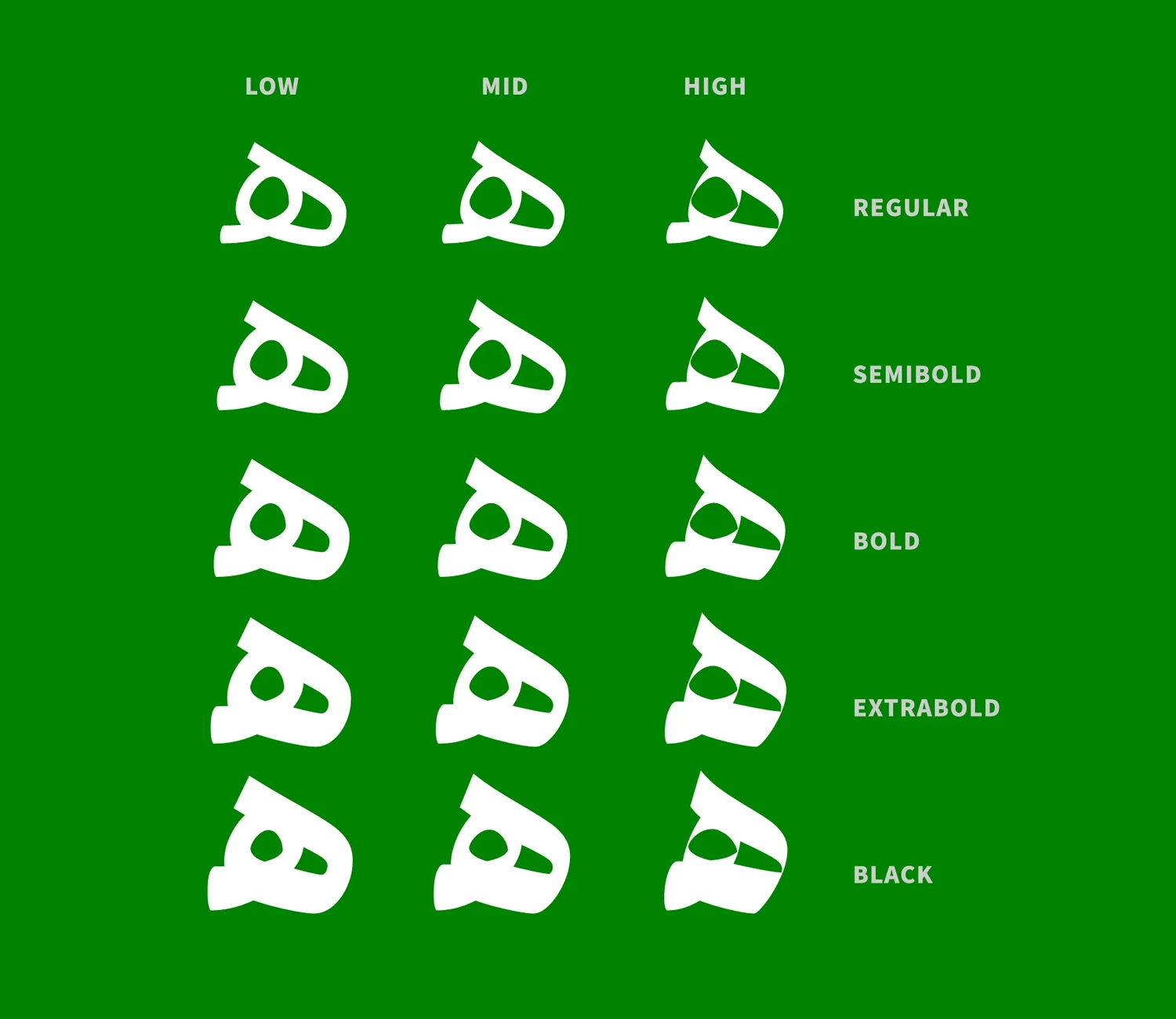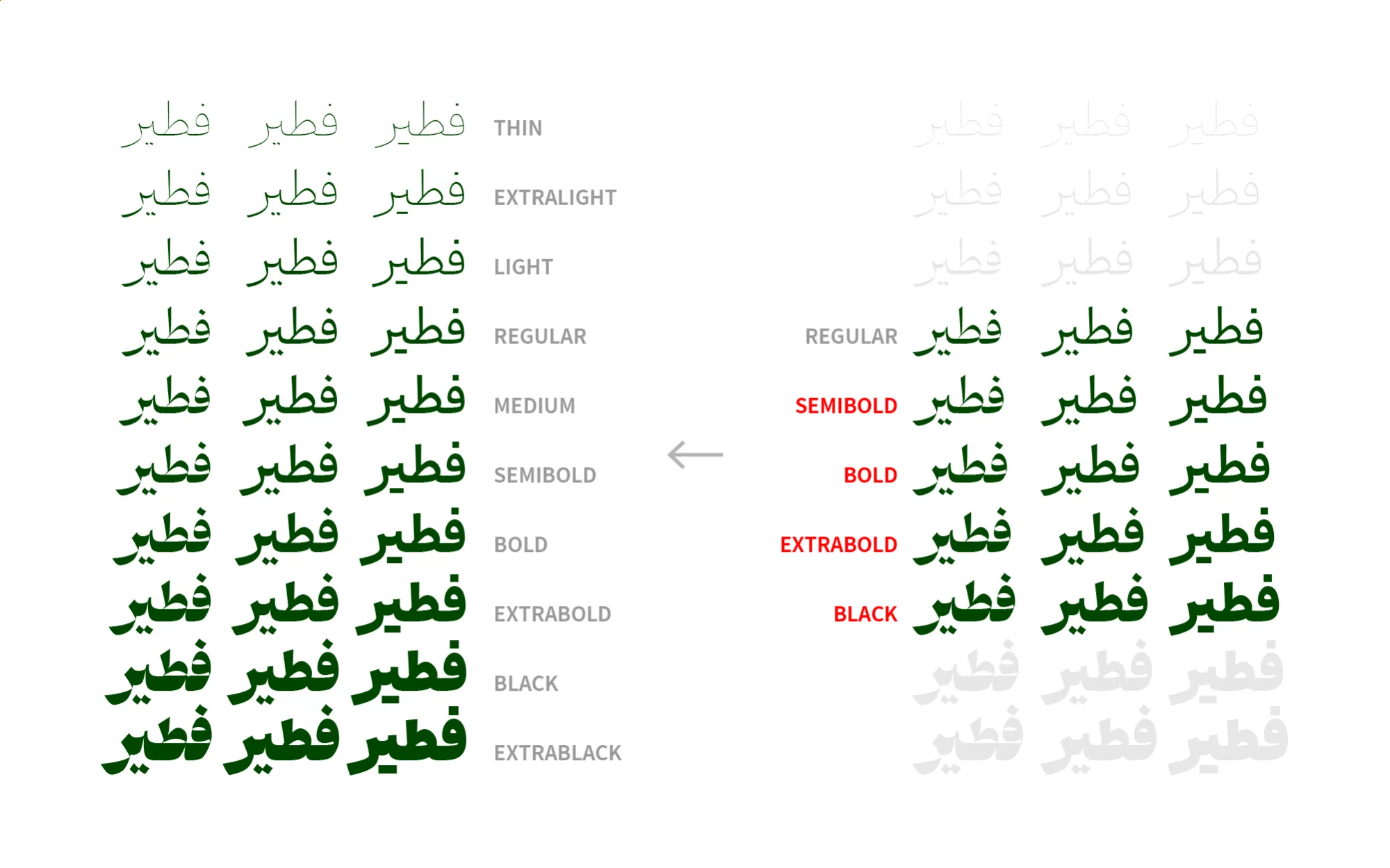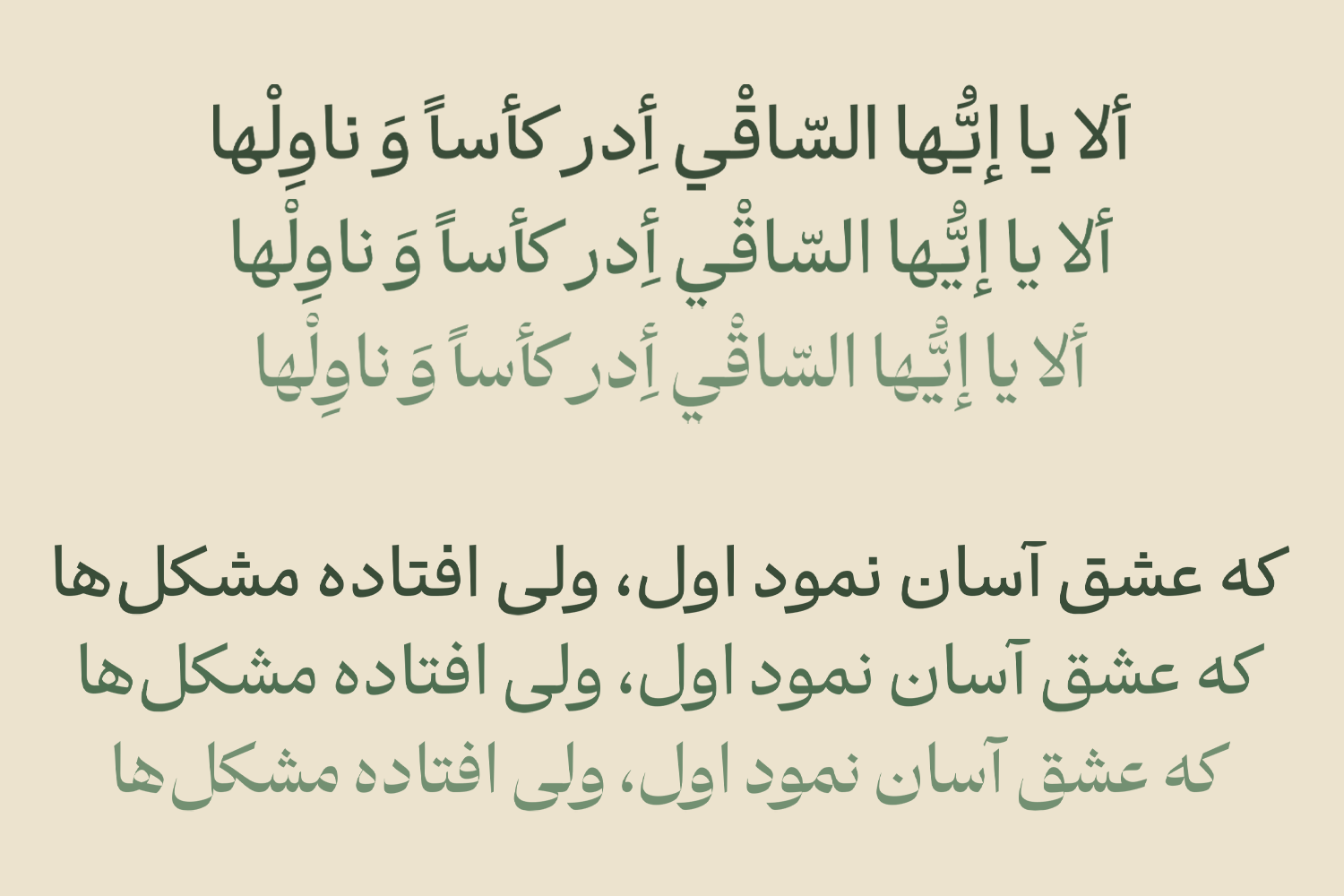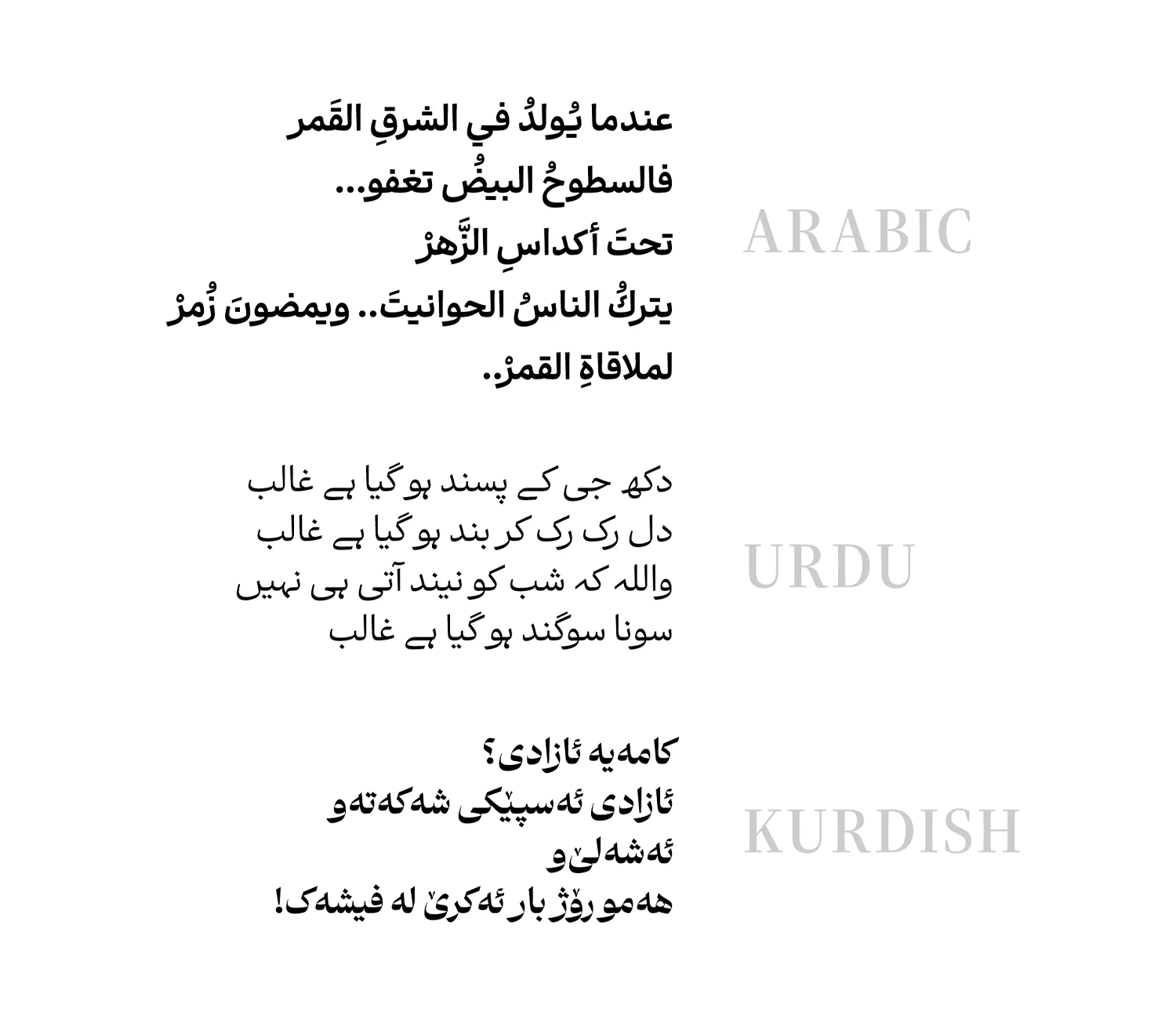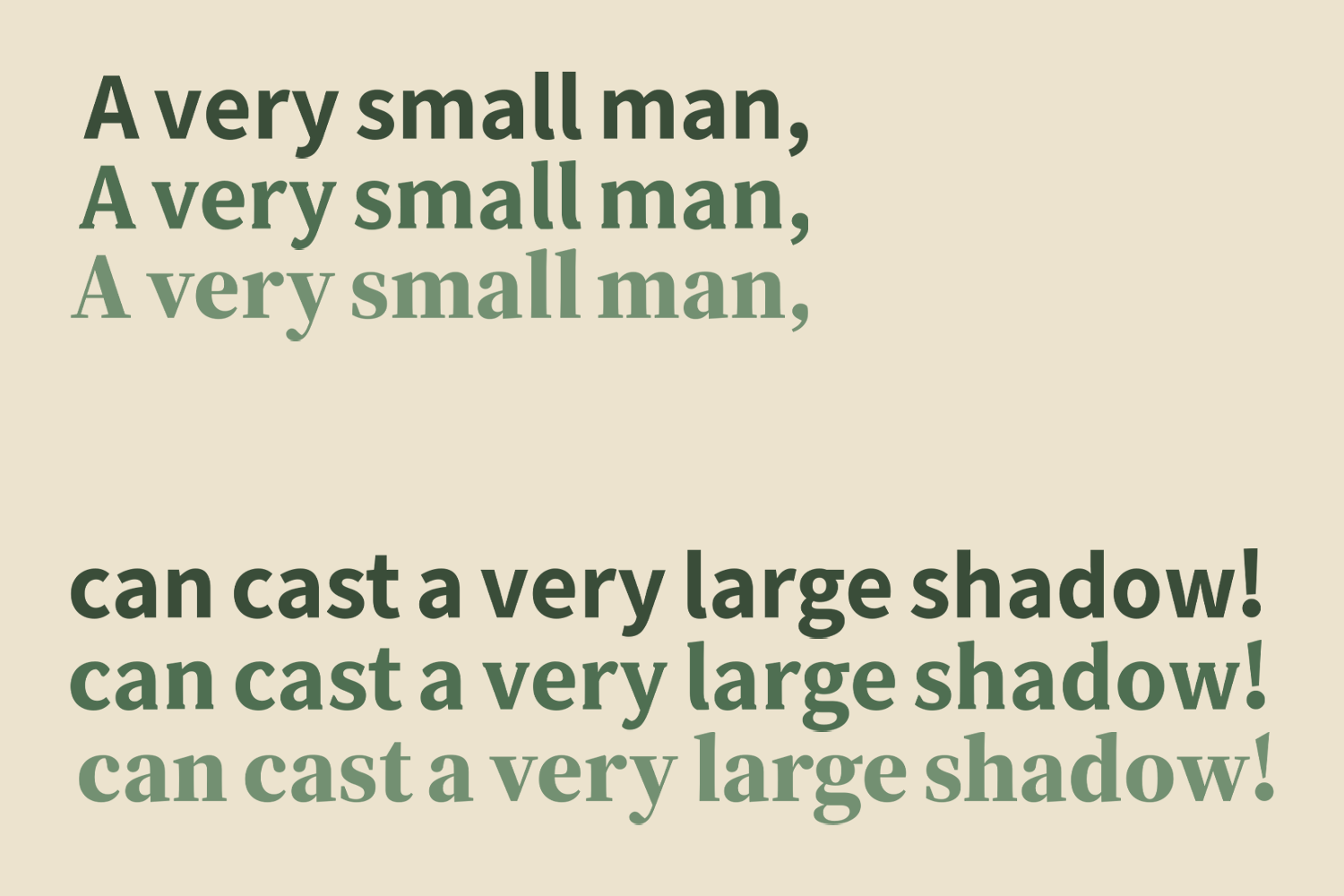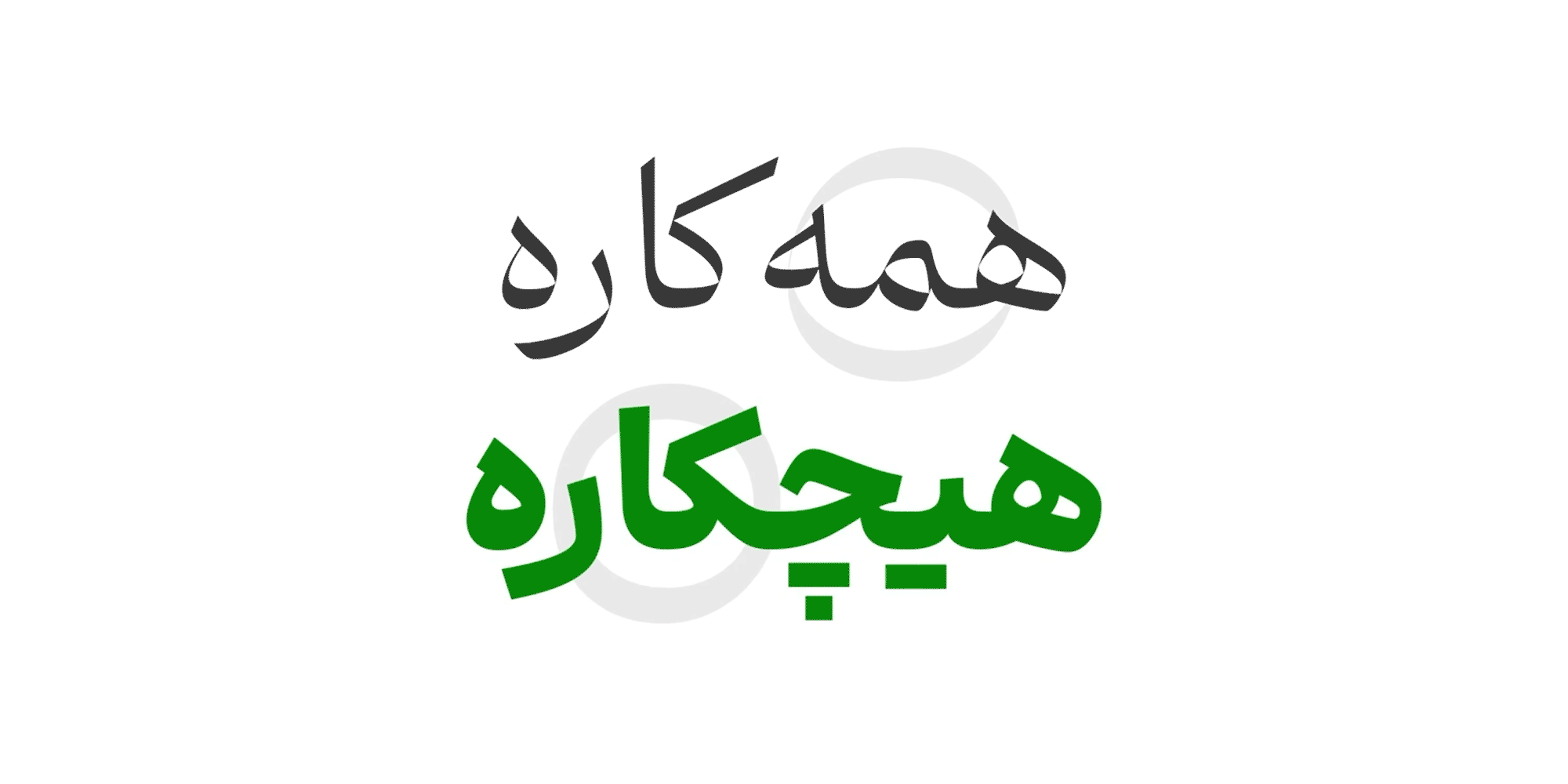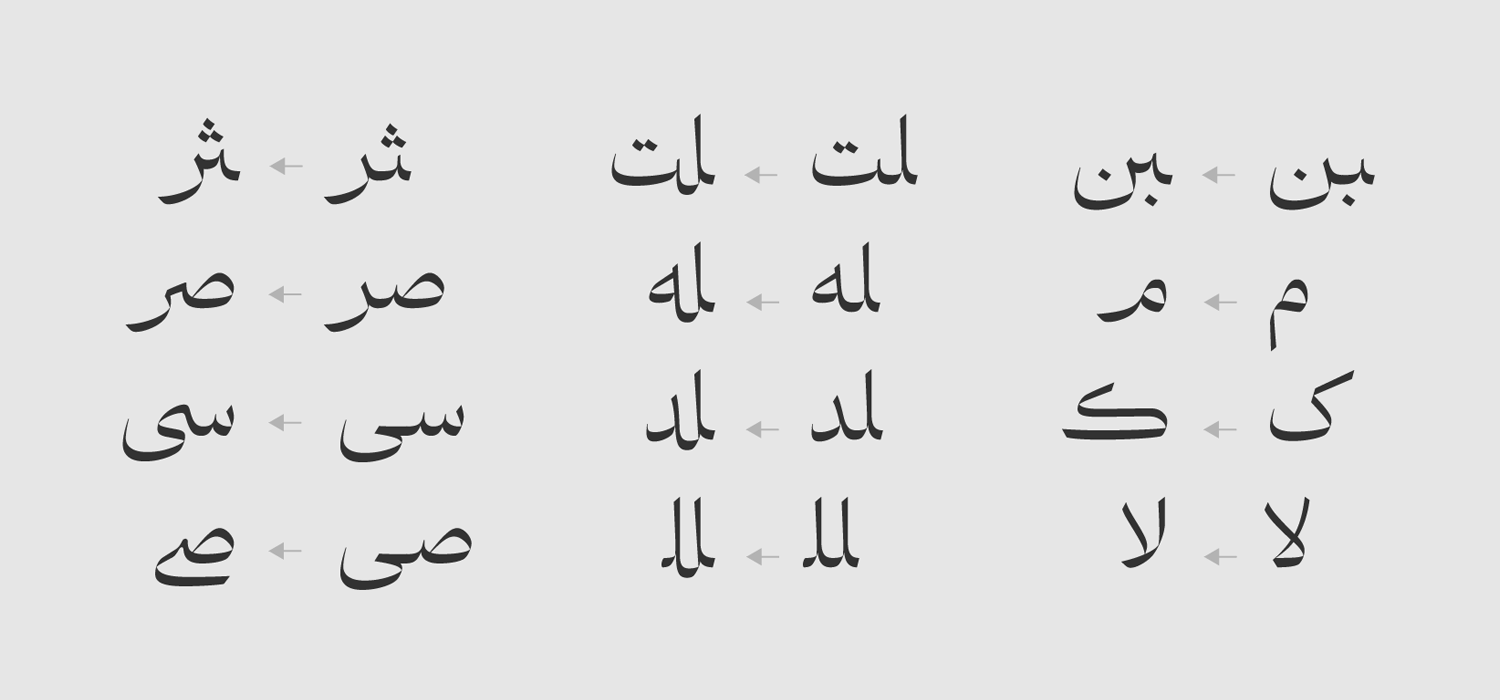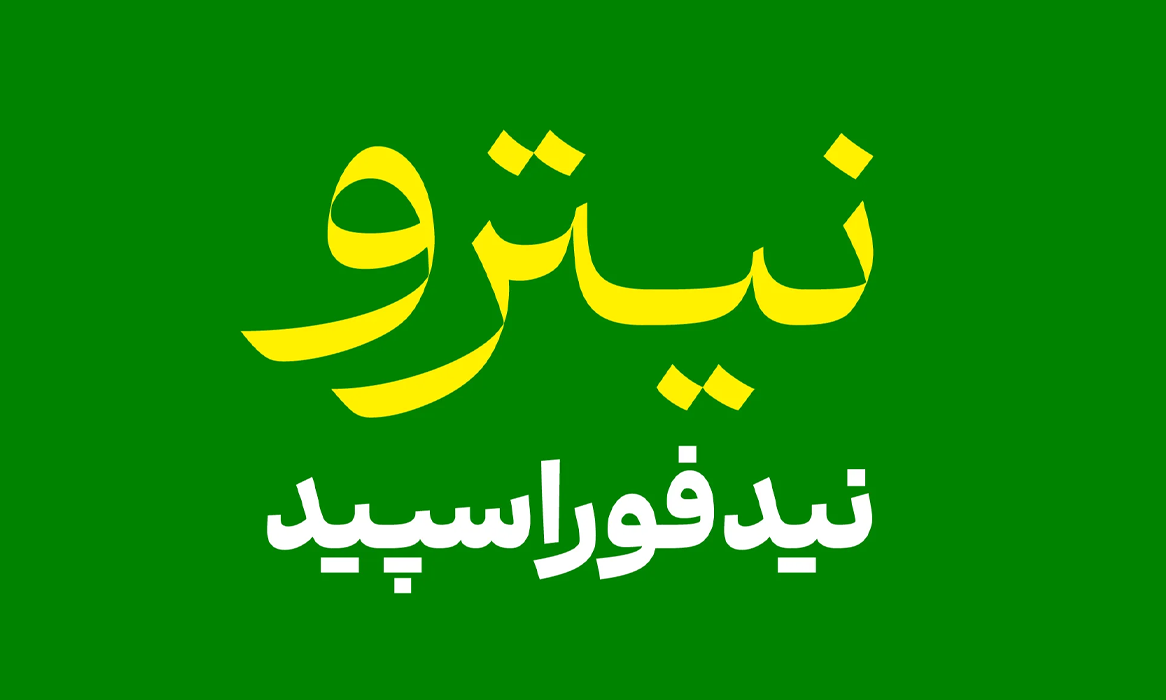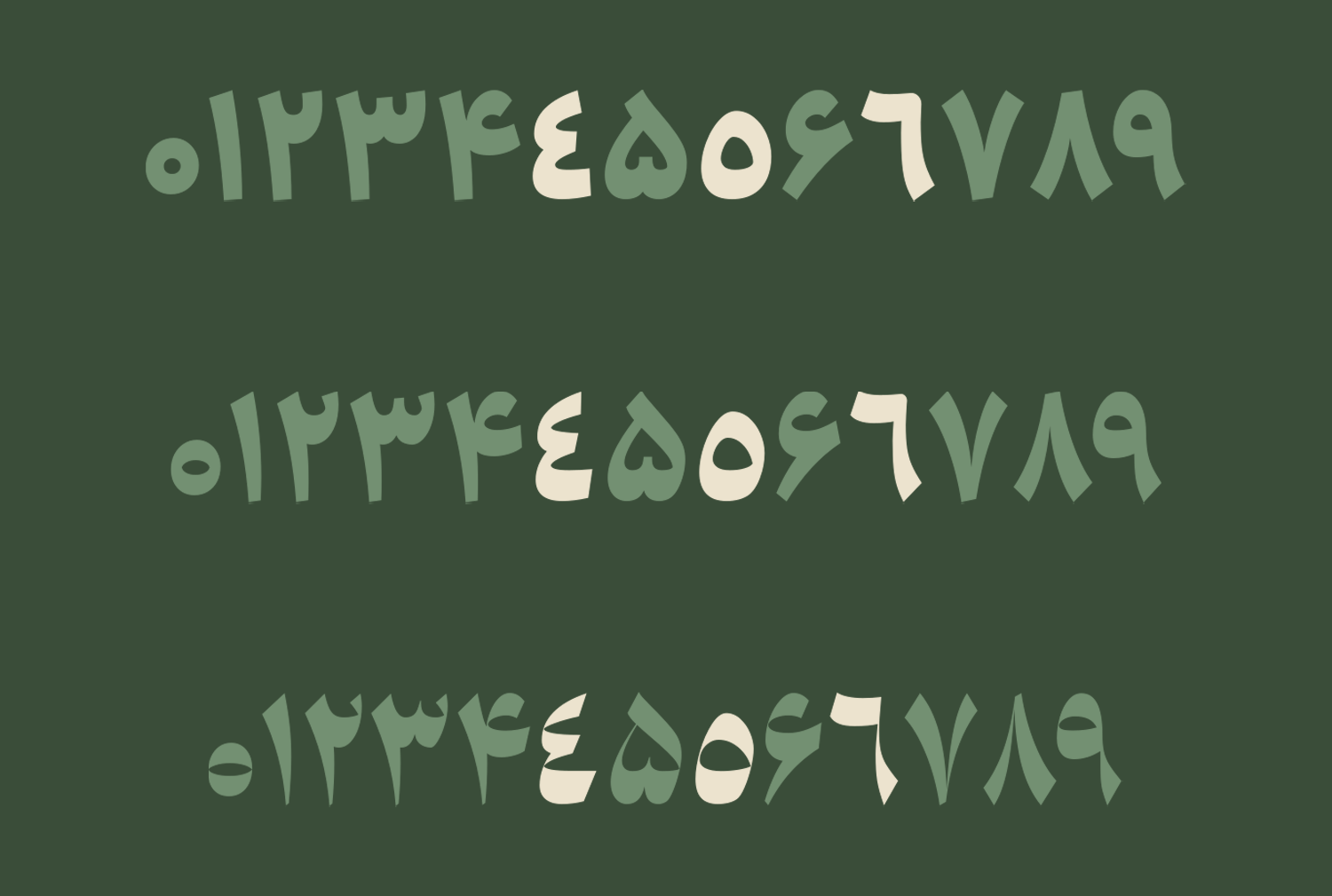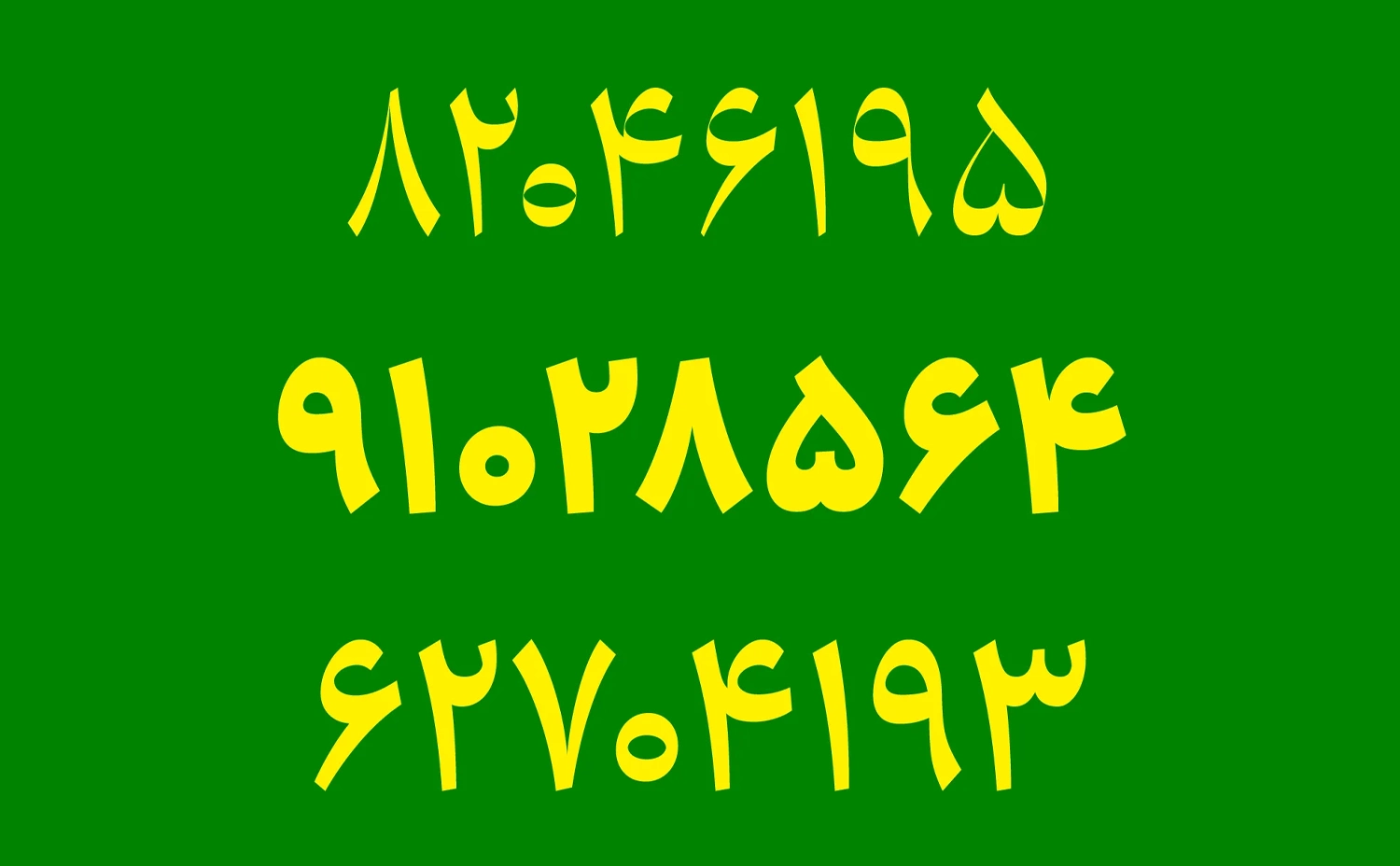
فونت ابر (Abar)
فونت ابر یا ابَر (به انگلیسی: Abar) یک فونت مناسب برای رابط کاربری و فضای دیجیتال است که بر خلاف سایر فونتها از ۳ سبک استایل مختلف که هرکدام دارای ۵ وزن گوناگون هستند پشتیبانی میکند. این فونت با ترکیبی از خط نسخ و سنس ایجاد شده که برای همین حس و حال یک قلم معاصر و بهروز را ایفا میکند. فونت ابر رایگان نیست و با توجه به تنوع وزنی ۱۵ تایی در کنار ترکیبات جایگزین و نسخه وریبل که دارد، در ۳ بسته قابل خریداری است.
رضا بختیاری فرد این فونت را با الهام از خط محقق طراحی کرده است که پشتیبانی کاملی از زبانهای خاورمیانهای متکی بر رسم خط فارسی و زبان انگلیسی دارد. با توجه به سبک طراحی این قلم با ترکیبی از خط نسخ و سنس، ساختاری بسیار نرم، دلنشین و صریح دارد که میتواند برای طراحی رابط کاربری در فضای کسب و کار آنلاین، انتخابی عالی باشد.
در ادامه این نوشته از سایت فونتچی به نقد و بررسی فونت ابر خواهیم پرداخت؛ قلمی که میتوانید با دسترسی به ۱۵ وزن مختلف که در قالب ۳ سبک طراحی شدهاند، ساختاری رسمی، ملایم یا نرم به متون خود بدهید. از این قلم میتوانید در متنهای کوتاه همچون عناوین گرفته تا متنهای بلند در فضای چاپ یا دیجیتال استفاده کنید.
در فونت ابر همانطور که از نامش مشخص است، با یک ابرفونت مواجه هستیم. ابرفونتی که تا بهامروز نظیر آن در بین فونت های فارسی مشاهده نشده است. این فونت خانوادهدار از ۵ وزن مختلف پشتیبانی میکند که هر یک دارای ۳ سبک بوده و در مجموع با قلمی در قالب ۱۵ وزن مختلف مواجه هستیم.
جدایی از وزنهایی که این قلم دارد، نسخههای مختلفی همچون نسخه مخصوص اعداد فارسی، نسخه بدون حروف لاتین و نسخه وریبل را در خود دارد که وجود چنین ساختارهایی آن را به یک فونت تماما حرفهای تبدیل کرده است.
در طراحی این فونت به خط محقق زیاد نگاه کردم. صلابت و ظرافت توأمان این خط مسحورم میکند. کشیدگیهای پاشنهها و کاسهها به این خط جلوهای شاهانه داده است.
طراحی فونت ابَر را مهر ۹۸ شروع کردم، تکهتکه و بهطور نامنظم، سر حوصله به تکتک فرمها و زوایا پرداختم و سمبادهکشی کردم. هدفم طراحی خانوادهی بزرگی بود، و هست؛ که شخصیتها و سبکهای مختلفی داشته باشد و نیازهای زیادی را پاسخ بدهد. ابَرفونتی باشد کارآمد و خواستنی. این خانواده بزرگتر خواهد شد.
این فونت در ۳ سبک و ۵ وزن در سال ۱۴۰۱ طراحی شده است و برای زبان لاتین از فونت اوپنسورس Source استفاده کردم، با کمی دستکاری.
رضا بختیاری فرد؛ طراح فونت ابر.
سبک طراحی و وزن فونت ابَر
تمامی ۱۵ وزن فونت ابر متشکل از ۳ سبک مختلف هستند که آنها را به ترتیب با نامهای Low، Mid و High میشناسیم. هر یک از این سبکها از نظر ظاهری دارای ساختاری هستند که به فونت ساختاری رسمی، میانهرو و نرم را داده است.
بهطوری که هرچه از سبکهای پایین به سبکهای بالاتر برویم، ساختار فونت از نظر نرمی و دوستانه بودن بیشتر خود را نشان میدهد. این موارد با ایجاد تغییرات در بخشهای مختلف حروف همچون ضخامتها، پاشنهها، گوشهها، گردیها و چشمیها ایجاد شده است.
در نسخه High فونت ابر شاهد بالاترین مقدار نرمی برای حروف هستیم. ضخامت فونت در زوایا به کمترین حد خود رسیده و به مویی بند است که چنین ساختاری را پیش از این در فونت دوران مشاهده کردهایم.
یا در سبک Low فونت ابر که شاهد شخصیت رسمی و قاطع این قلم هستیم، ضخامت، گردیها، گوشهها و چشمیها ساختاری کاملا صریح از خود نشان میدهند و سخت است که بخواهند با شما رفتاری صمیمانه داشته باشند.
پشتیبانی حرفه ای از ۵ زبان متنوع
فونت فارسی ابر با توجه به ساختاری که سایر زبانهای خاورمیانهای مثل عربی، کردی و اردو دارند از این زبانها پشتیبانی کاملی دارد. در تمامی زبانهای خاورمیانهای میتوانید از ساختار کاملا درست هر زبان برای حروف استفاده کنید، طوری که در تضاد با صفحه کلید انتخابی شما نباشد.
به عنوان نمونه حروف «ک، ی، ه، ؤ، ئ» در زبان عربی یا حروف «ﮧ، ﮩ، ے» در زبان اردو کاملا متمایز از حروف فارسی بوده و دارای گلیف اختصاصی خود هستند. در حالی که سایر حروف مشترک از یک گلیف بهره میبرند و همین مسئله این قلم را به فونتی کاملا استاندارد تبدیل کرده است.
در این خصوص علاوه بر اینکه اعراب و برخی گلیفهای تزئینی که در هر سه زبانهای عربی، اردو و کردی آنها را بهوفور میبینیم در قلم پیادهسازی شده است؛ بلکه از برخی حروف زبانهای اردو نیز بهمنظور حروف جایگزین استفاده شده تا فونت ابر را به فونتی نمایشی و دوستانه نیز تبدیل کند که در ادامه بیشتر آن را بررسی خواهیم کرد.
در فونت abar انگلیسی از فونت اپنسورس Source استفاده شده است که ساختار نزدیکی با قلم دارد. اما به منظور ایجاد ارتباط بهتر برای استفاده همزمان دو زبانها، کمی تغییرات برای حروف انگلیسی اعمال شده است.
فونت حرفه ای وریبل ابر
ویژگی دیگر فونت ابر پشتیبانی از نسخه متغیر وریبل (Abar Variable Font) است که به شما این امکان را خواهد داد به تمامی وزنهای این فونت در قالب یک فایل فونت دسترسی داشته باشید.
فونت وریبل ابر از تمامی ۳ سبک و ۵ وزنی که هر یک دارند پشتیبانی کرده و علاوه بر این سایر امکاناتی که این قلم نظیر پشتیبانی از اعداد فارسی و عربی، حروف جایگزین و کاراکترهای خاص دارد پشتیبانی میکند.
فونت وریبل ابر دارای دو متغیر است: